Font chữ tròn mập là font có các góc chữ được bo tròn, nét mềm mại mang phong cách friendly, approachable được sử dụng rộng rãi trong thiết kế bao bì đồ chơi trẻ em, túi giấy cafe và in ấn cho thương hiệu kids. Font chữ bo tròn với đặc điểm dễ thương, thân thiện tạo cảm giác gần gũi, vui tươi.
Ở bài viết này, In Viva giới thiệu font chữ bo tròn góc việt hóa và font bo tròn việt hóa với hơn 12 mẫu miễn phí từ Google Fonts phù hợp cho thiết kế thân thiện.
Font chữ tròn mập (rounded) là gì?
Font chữ tròn mập (rounded font) là font có các góc chữ được bo tròn thay vì vuông góc. Rounded font tạo cảm giác mềm mại, friendly, playful – ngược lại với font vuông cứng cáp, mạnh mẽ.
Cách tạo rounded font: Designer lấy font gốc (thường là geometric sans) và bo tròn tất cả các góc với radius đồng nhất. Ví dụ: Nunito là rounded version của một geometric sans.
Mức độ rounded:
- Semi-rounded: Bo tròn nhẹ, vẫn giữ một số góc. Ví dụ: Lato, Rubik. Cảm giác: professional nhưng friendly.
- Fully rounded: Mọi góc đều bo tròn hoàn toàn. Ví dụ: Nunito, Quicksand, Comfortaa. Cảm giác: playful, cute, kids-friendly.
Tại sao rounded font “friendly”:
- Psychology of shapes: Con người tiềm thức cảm thấy hình tròn = an toàn, mềm mại. Góc nhọn = nguy hiểm, aggressive. Rounded font khai thác tâm lý này.
- Childlike association: Trẻ em thường vẽ chữ với góc tròn (chưa precision motor skills) – rounded font gợi nhớ đến tuổi thơ, innocence.
- Approachable, non-threatening: Rounded font không imposing, tạo cảm giác dễ tiếp cận, không áp lực.
Bảng tổng hợp font chữ bo tròn góc việt hóa free từ Google Fonts:
Tên font |
Mức độ rounded |
Ứng dụng in ấn tốt nhất |
Nunito |
Fully rounded, 14 weights | Bao bì đồ chơi, sản phẩm kids, organic |
Quicksand |
Fully rounded, geometric | Logo cafe, bakery, friendly brand |
Comfortaa |
Fully rounded, ultra friendly | Bao bì trẻ em, educational toy, app kids |
Varela Round |
Fully rounded, simple | Nhãn sản phẩm natural, sticker cute |
Rubik |
Semi-rounded, professional | Bao bì wellness, health, lifestyle |
Josefin Sans |
Semi-rounded, elegant | Bao bì organic luxury, spa natural |
Baloo 2 |
Fully rounded, chubby | Logo kids brand, poster sự kiện trẻ em |
Fredoka |
Fully rounded, bold playful | Bao bì snack kids, juice box trẻ em |
Signika |
Semi-rounded, signage | Biển hiệu, wayfinding, menu |
Lưu ý: Font rounded rất friendly nhưng không phù hợp mọi brand. Không nên dùng rounded cho luxury brand, law firm, finance, serious B2B.
Ứng dụng font tròn trong bao bì thân thiện
Font chữ tròn mập với phong cách friendly được ưa chuộng:
- Perfect cho kids product: Rounded font là “ngôn ngữ” của trẻ em – mềm mại, an toàn, vui tươi. Tất cả brand kids nổi tiếng đều dùng rounded.
- Organic, natural association: Bo tròn gợi liên tưởng đến thiên nhiên (lá cây, hoa, quả) – phù hợp organic food, natural skincare, eco product.
- Friendly, approachable brand: Startup muốn gần gũi user, cafe muốn ấm cúng, bakery muốn homey – rounded font là lựa chọn top.
- Reduce formality: Khi brand muốn less corporate, more human – rounded font giảm khoảng cách giữa brand và customer.
Font tròn mập xuất hiện trong nhiều sản phẩm in ấn:
- Bao bì đồ chơi trẻ em: educational toy, building block, puzzle, board game.
- Túi giấy cafe, bakery: coffee shop neighborhood, artisan bakery, pastry shop.
- Bao bì thực phẩm kids: baby food, kids snack, juice box, yogurt.
- Nhãn sản phẩm organic: organic baby care, natural soap, eco cleaning.
- Bao bì mỹ phẩm natural: natural skincare, organic haircare, eco beauty.
- Menu nhà hàng family: family restaurant, kids-friendly cafe, ice cream shop.
- Poster sự kiện trẻ em: kids festival, playground, summer camp.
- Brochure giáo dục: kindergarten, preschool, kids learning center.
- Hộp quà kids: children’s gift box, baby gift set.
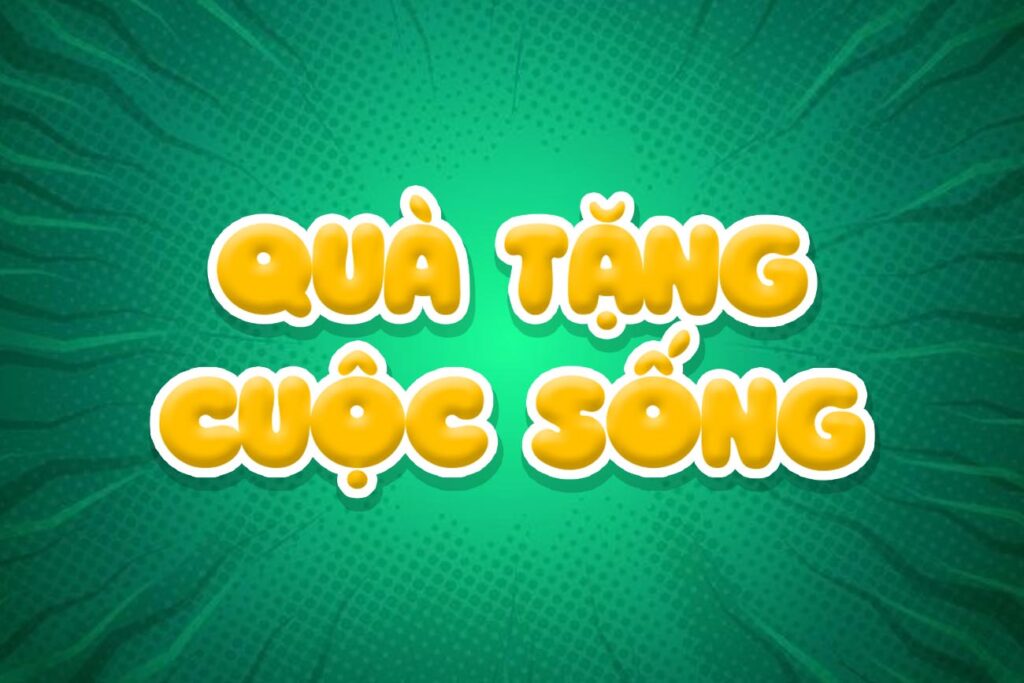
3. Rounded font có dễ đọc không?
Fully rounded (Comfortaa, Fredoka) khó đọc ở body text dài. Semi-rounded (Nunito, Rubik) dễ đọc hơn. Rule: rounded cho heading/logo, sans thường cho body.